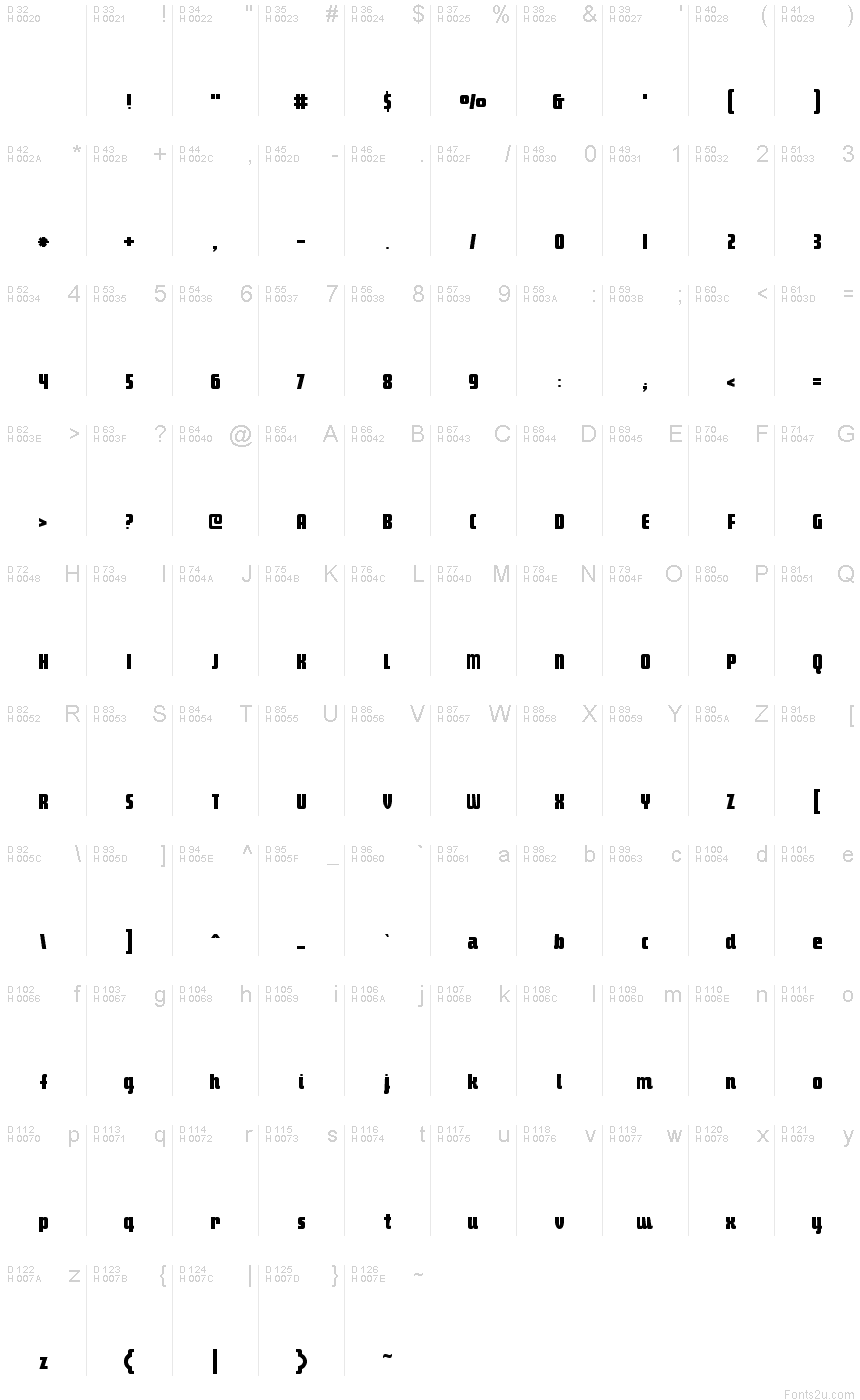
Makimango od Claese Kallarssona je bezplatné geometrické display písmo, které definují hutné, černé tvary a měkce zaoblené rohy, díky nimž působí písmena jako kompaktní nápisové bloky. Jeho rytmus vychází z hlubokých vertikálních řezů a širokých, tupých křivek, které designu dodávají pevnou a vážnou přítomnost, aniž by vypadalo mechanicky.
Tato kompaktní silueta dává krátkým titulkům silnou roli na plakátech, hudebních letácích, skate grafikách, skicách log a obalech, kde pár slov potřebuje zabrat prostor. Dává smysl také pro úvodní obrazovky aplikací nebo odvážné webové nadpisy, zejména pokud hledáte zaoblenou hmotu a těsně uspořádané tvary namísto neutrálního bezpatkového písma.